种招式我们“刚柔并济”分为灵感篇与方法篇,从字体设计最初的思考入手,看看字体设计的灵感都是从何而来,又是如何一步步实现有逼格的字体。希望本期的分享能让你面对字体,春暖花开~
字体设计是一件非常有趣的事情,但是对于一些朋友来说面对字体设计时总有些小烦恼。所以今天和大家分享的更像是一个字体设计的“过程”,七种招式我们“刚柔并济”分为灵感篇与方法篇,从字体设计最初的思考入手,看看字体设计的灵感都是从何而来,又是如何一步步实现有逼格的字体。希望本期的分享能让你面对字体,春暖花开~
对了,之前《零基础的字学之路》那篇帖子有介绍过一些方法,这次算是加料升级。好,让我们开始吧!
灵感这东西其实是看得见摸得着的,因为它就存在于我们身边的点滴。我常常被问及到:字体设计到底该怎么去做,类似这样的问题,其实在我看来这个问题可以拆分成两个问题:一个是如何想?一个是怎么做?下面我们就具体的了解下如何去找寻字体设计中的灵感。
在我们生活中不经意间可能就会有一些有意思的想法“蹦跳”出来,这些想法其实是尤为珍贵的,或许那一刻你会觉得有些可笑甚至有些荒唐,但是谁又敢保证未来的某个日子里,在办公桌前绞尽脑汁想点子的你不会用到?!所以要善于把一闪而过的灵感“储藏”起来。
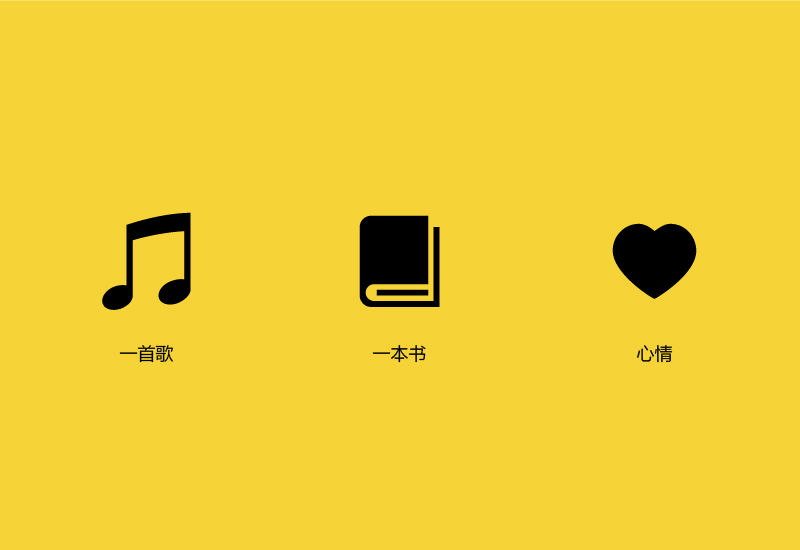
很多时候我们会被一首歌打动,会为一本书里某一句话而感动,又或者是让某一件事某一个人左右了自己的心情...总之,生活处处有惊喜,当然也会有各式各样的小状况,其实这些都可以作为你字体设计中点燃灵感的小火花。字体不是简单地笔画堆叠,更多的需要我们将自己的情绪融入其中。
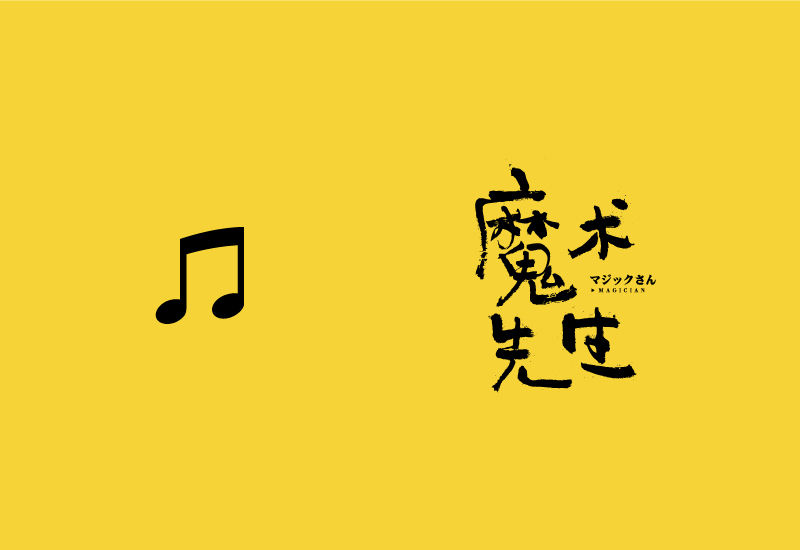
比如某个周末听杰伦的歌竟让我有点“怀旧”感叹日子过得飞快,于是做了一组杰伦歌曲的字体。不用去计较字体什么形式风格,能够表达你当时的情感便可。
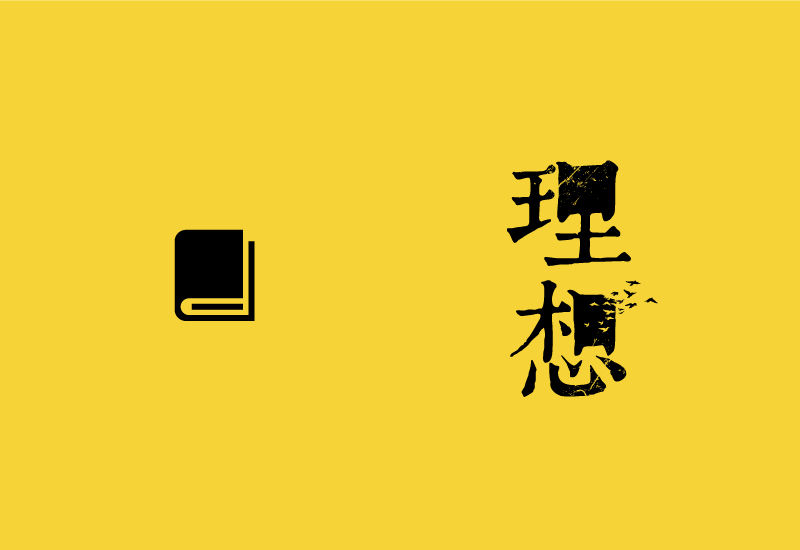
或者快毕业了又看到老罗那本《我的奋斗》竟然让我思考起我的理想,虽然那时我将以毕业,还来不及高攀理想,就掉进现实的漩涡。
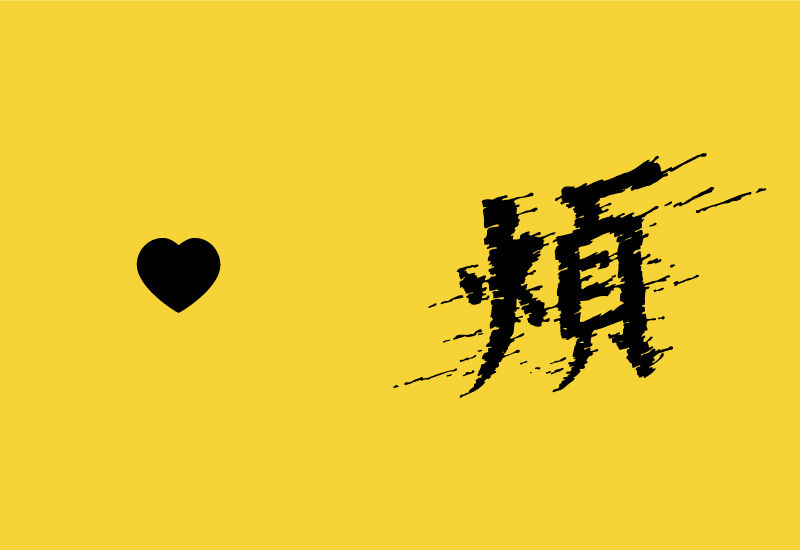
当然自己烦躁的时候,也可以通过字体来宣泄情绪。你应该试着戴上耳机,不理会周遭,慢慢享受与字体的单独“约会”。
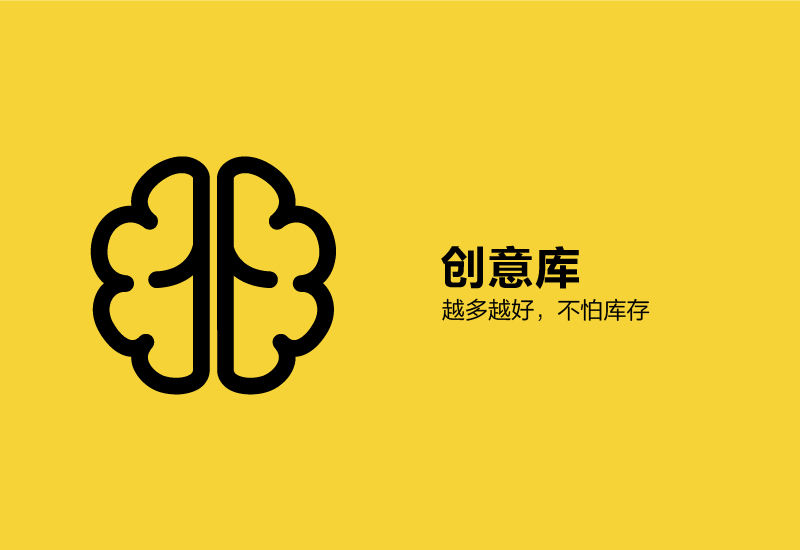
当你积累的够多,慢慢的就会在你脑海里形成一个字体设计创意库,在遇到具体的字体设计任务时,你便会在自己的脑海里先检索一遍,虽不能说百分百会有匹配,但最起码你会变得从容许多。
模仿是学习进步一个很好的方式,既要引进来更要走出去。我们不管是做字体还是做logo或者其他东西,我们都习惯先在网上找寻相关的设计作品,当然平时浏览设计网站也会发现很多很棒的设计作品,这时候你是一扫而过?还是右键保存?还是尝试着去研究一下?
在字体设计方面遇到好的作品我建议大家用笔在纸上临摹一下,这要比单纯的看更容易理解字体的结构、笔画特征和一些细节性的东西。当然加让你的一些想法理解那是再好不过了。
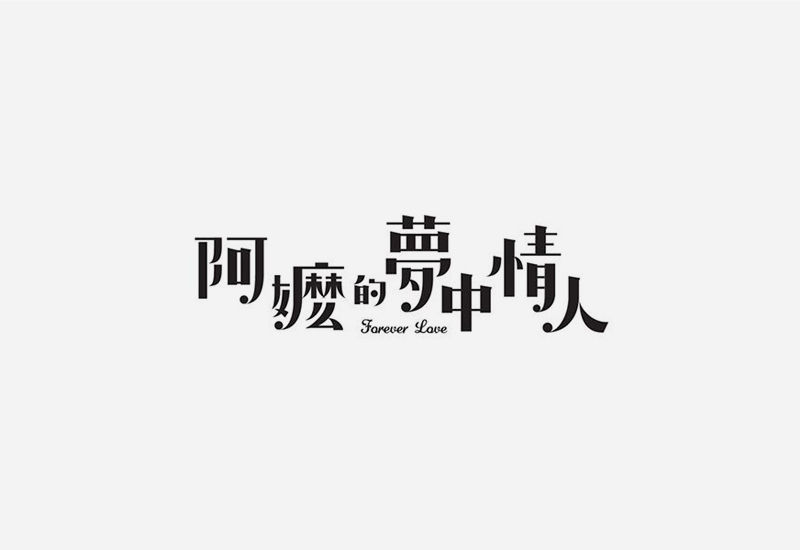
这组字是之前在网上看到的字体,我们来消化一下,首先字体特征比较明显,横笔较细,竖笔较粗,两者悬殊较大,然后一大亮点就是一勾一撇处酌情添加了一个圆点,很有意思,然后整组字的排列方式就比较的不规则,错落有致。
这是消化吸收了上一组字的风格,重新做了这样一组标题字,其实也没有太过复杂,尝试去做就对了。其实这就是一个典型的模仿在创造的过程,记住我告诉你的方法,先在纸上临摹一遍,然后趁热打铁再尝试新的字组设计,是不是感觉66的?还不行,那就在多临摹几遍吧!
如何想解决了,下面就是教大家怎么做了。方法有很多,我列举了最为基础实用的几种方法与大家分享,其实每种方法对应的是无数种字体设计的可能,很多惊喜等你发现。
块面组合法是字体设计中最为基础也是最常规的设计方法。块面组合法基本说来就是以几何块面为基本的笔画搭字,然后再进行深入的调整和变化,呈现出不同形式感觉的字体。
具体来讲,块面组合法就是先使用矩形工具设定好笔画的粗细,然后进行组合造字,构建好基本的结构字形,接着做进一步的调整和细化,尝试对一些笔画 进行断笔、共用和删减等处理,不断丰富字体的细节特征。此种方法操作简单,且易于控制,特别适用于初学字体设计的朋友,可以作为字体设计的入门方法进行不 断地尝试与练习。
01.使用矩形工具确定基本的笔画粗细,然后进行字体的搭建。这一步我们可以统一笔画粗细,或者根据字形需要笔画的粗细随机应变。这组字里我们用的的基本笔画就是长宽不规则的,笔画较密集的地方副笔适当细一些。
02.而字形结构上我们也做了相对应的变化,以“象”字为例,笔画的断连比较明显,并且在不影响识别性的原则下重新归纳了个别笔画的走势。
03.最后使用勾勒出一个城市建筑轮廓并辅以英文小标题,使其趣味性和整体性更佳。
类似的方法笔画的粗细、字形结构的不同、组合方式的改变都可以创造出分割多样的作品。
如果把“块面组合法”想象成小游戏“俄罗斯方块”,那么“线段连接法”就如同“贪吃蛇”一般灵活多变。这种方法主要应用软件中的”钢笔”工具,通过改变线段粗细、曲直和断连关系,从而设计出不同风格的字体。
灵活多变是线段连接法最大的特色,除了基本的直线,可根据实际需求来变化曲线和折线等。所以不管是横平竖直的常规方块字体,还是曲线夸张的风格字 体,都可快直接快速地勾勒出来,这一步选用钢笔工具完成即可;当确定好了基本字形,再调整描边的粗细和端点的曲直,反复进行调试和对比,使字体达到最佳的状态。
01.使用”钢笔”工具勾勒出字体的骨骼。字体设计不是一步到位,而是需要反复的对比与调整,所以这一步只需勾勒出基本的想法构架便可。
02.接着就是深入的调整了,我们将笔画加粗并把描边端点改为圆形,笔画直角改为圆角字体,使其显得更加有亲和力;修改细节,统一增加字体高度,相较于之前显得更加瘦长,个性特点也更加鲜明。
03.最后一步,拼音上选择了一款笔画端点同样圆润的字体进行组合搭配。这样简单几步线段连接法就造出来我们想要的字体效果。
需要特别注意的是,当整个字笔画都是以均匀的线段为主时,线段之间的穿插分布切忌过密过疏,尽量保持匀称,适当增加字体内部空间,透气性佳整体才会更显轻盈雅致。
对于一些需要表现手工质朴感的字体,手绘描摹法再合适不过了。通过其名称不难理解,手绘描摹法大概就是先在纸上手绘出完整的字体样式,然后录入电脑,将手绘稿在软件中进行描摹绘制,并适当加以修饰。
手绘相较于电脑绘制总有不一样的感觉和优势,特别是对于一些复杂的字体设计,手绘更加灵活效率也更高一些,先用手绘再通过电脑将字体进行还原,这样手工质朴的感觉可以得到最大化保留。
01.第一步就是先在纸上绘制出整个字体,对于一些复杂的字体特别需要静下心耐心绘制。这里这组字体其实就是多了一些“飞溅”的效果,字形上倒没什么特别。
02. 将手绘好的字体放入软件中进行描摹,并修饰轮廓和细节。一般的我会使用手机直接将绘制好的稿子拍下来,然后在进行软件的描摹,当然直接扫描效果会更好。
03.最后填色完成设计,你也可以再使用Photoshop软件进行处理,使字体效果上更加出色,视觉冲击力更足。
这种方法重点在于纸上的手绘,字体形式和细节上的变化和处理基本都在纸上完成,软件描摹则尽量地还原手绘稿的原貌,当然最后对于细节上的问题也要及时地加以修正。
字库内的字体结构严谨规矩,因其主要以方便阅读为目的,所以缺少一些个性的释放。而字库改造法就是以中文字库内的字体为设计基础,加以改造和修饰,这样不管是在形式上还是风格上都有别于原有字体,个性鲜明突出,焕发新活力。
老实说这是一种比较“偷懒”的设计方法,却也是一种比较有效和快速的设计方法,特别是在一些电商行业的字体设计中会常用到此方法。归纳下来字库改 造法其实就是对原字体进行加法与减法的整合,加法就是指改变原有字库字体的笔画特征,并增加笔画细节,而减法则是指将原笔画进行合理的断笔,巧妙的共用, 灵活的删减,最终达到简化的目的,以一加一减的形式完成对字库字体的改造。
01.我们选用了细明体“算命先生”四字为改造的基础字形,大家可以根据自己的需求来选择需要改造的字体,字体虽不同但方法基本一致。
02.接下来将字体扩展然后做拆减处理,对字体进行重构。这一步其实就是考验我们想象力了,不一定只是拆减,你也可以在原笔划上增添新的元素等等,让字库字体彻底酷起来。
03.细节处理与调整,这一示例主要是将直角转变为变圆角,借用查件Xtream Path即可快速实现,其他无需做太大的修整。在做字体设计的时候不要一味追求过多的变化,不要每个笔画都要来个“九连环”,适可而止,当表达出字体意境时就及时收手吧。
在西文字库中有很多形式感非常强的字体,我们可以借用其中的字母充当中文的基本笔画,加以融合改造,制造出别有韵味的中文字体。
在使用此方法进行字体改造和设计时,首先把西文里的大小写字母全部展开以备用,然后选取其中的完整字母或是截取字母当中的某一部分进行中文字体的 搭建。有时候会遇到其中的某些西文笔画并不完全符合传统中文的笔画走势,像这种情况下可在不影响识别性的原则下,打破常规,多保留原有西文字体的特征,当 然也并不是所有的笔画都是完全的合适,具体到一些笔画可根据西文制造出相应的中文笔画。
01.图为Chiller字体,比较随性、自然的手写字体。第一步就是一字排开,创建轮廓以备用。
02.做中文字体搭建。图中红色笔画部分为西文原字母,蓝色笔画部分是经过修改或局部截取的西文字母。本身英文字体就是手写形式且不规则,我们中文字体也保留这一特点,大家可以想象一下如果这几个字都是一般大小,字体本身的意境或许就没有现在表达的充分。
03. 加英文作为点缀,直接使用Chiller字体就可,放在一起是不是和谐的像一家人,相亲相爱。
总结下来就是以中文结构笔画为基本需求,灵活借用西文字体并对中文字体做以改变和调整,并保留西文特色,以达到西文中用的目的。
不管是灵感的构想或者是造字的方法,每个人都会有习惯的方式,仅此分享自己的一些小方法,不一定是非要按照如此的一个步骤;一个好的字体设计作品也绝非一步两步便可完成,更多的需要你不断地尝试、调整,当做得多了终会找到属于自己的方式与风格。
灵感、方法都告诉你了,勤快的你赶紧操练起来吧!